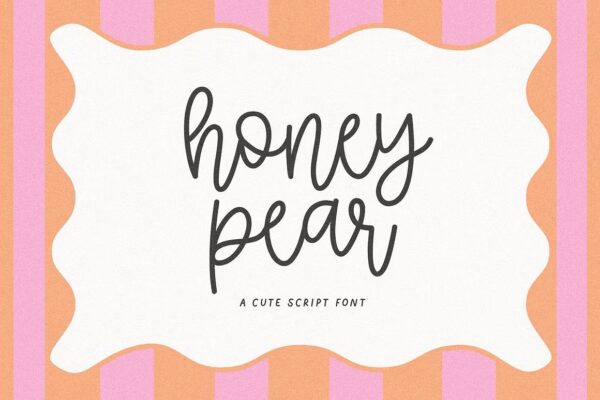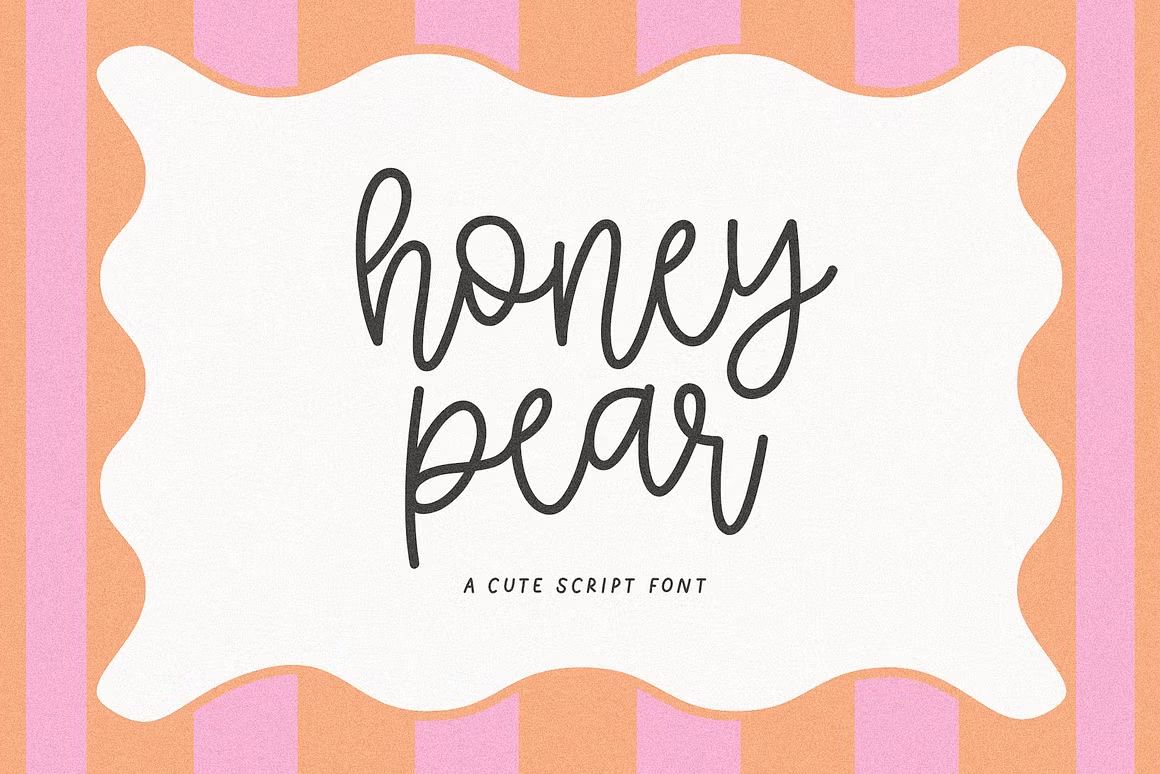
Honey Pear – Cute Script Font
Honey Pear adalah font script lucu dengan gaya tulisan tangan yang manis dan menggemaskan, sempurna untuk desain kartu ucapan, logo, undangan, dan proyek kreatif bernuansa ceria dan feminin.
Honey Pear adalah font script imut dengan sentuhan tulisan tangan yang manis dan lembut. Desainnya yang playful namun tetap rapi membuat font ini cocok untuk berbagai proyek kreatif seperti kartu ucapan, undangan, logo, kemasan produk, dan branding dengan nuansa ceria dan feminin. Honey Pear memberikan kesan hangat dan ramah pada setiap desain.
• Gaya script tulisan tangan yang cute dan friendly
• Cocok untuk undangan, kartu ucapan, logo, dan branding feminin
• Termasuk huruf besar, huruf kecil, angka, dan simbol lengkap
• Ideal untuk proyek cetak maupun digital bernuansa ceria dan menggemaskan